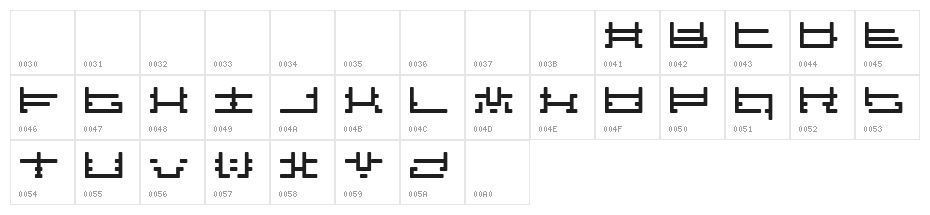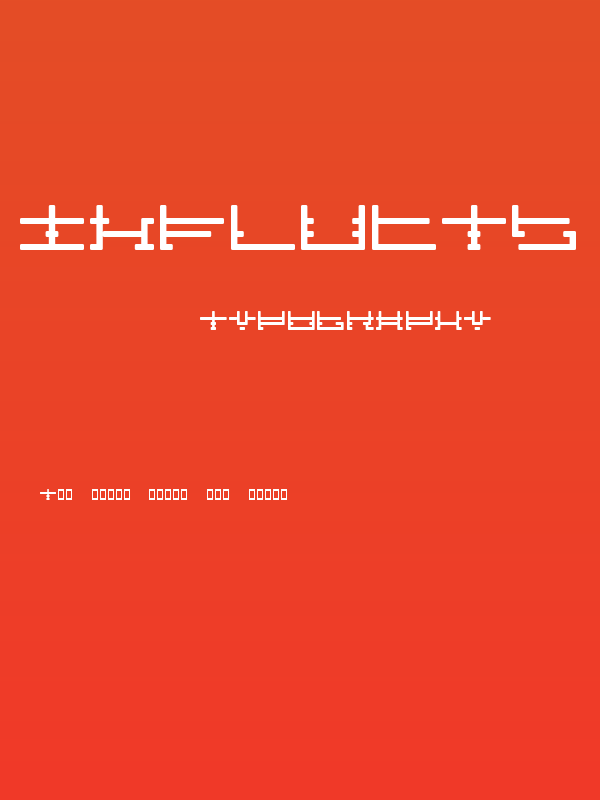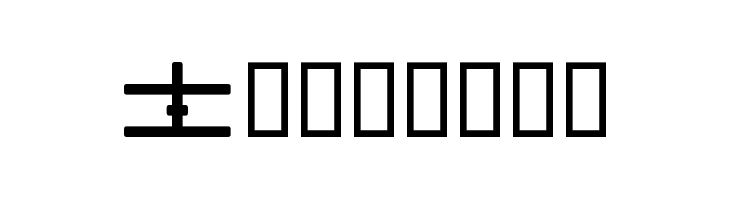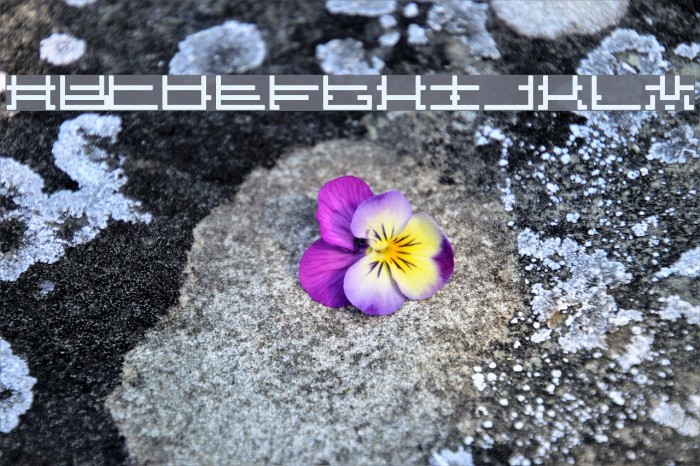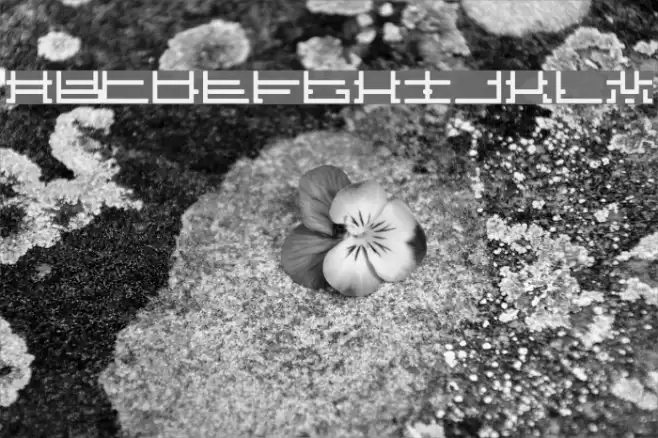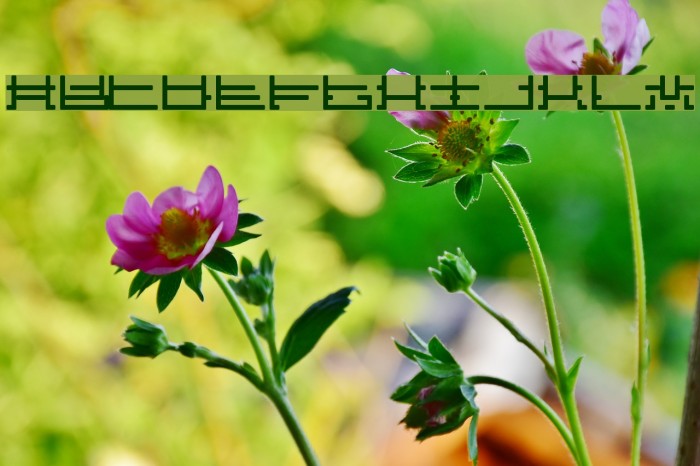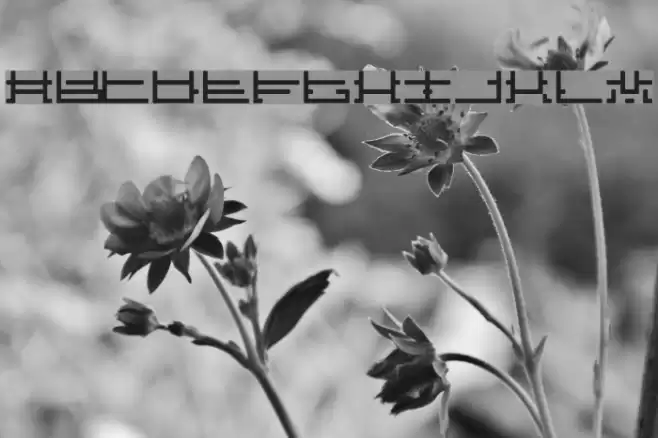
Influcts Font
| النمط العام | Futuristic, Abstract |
| مشاريع مقترحة | Ideal for sci-fi themed designs, video game interfaces, posters, and branding that seeks a modern and unconventional look. |